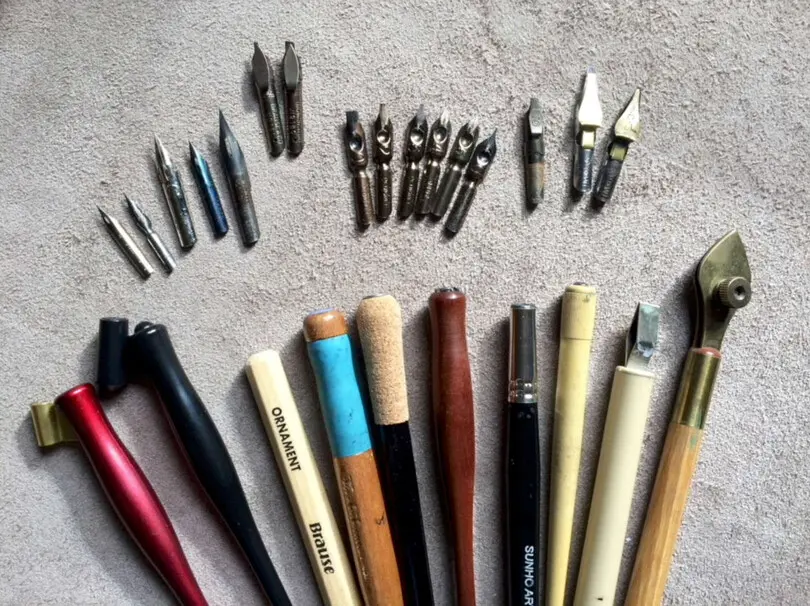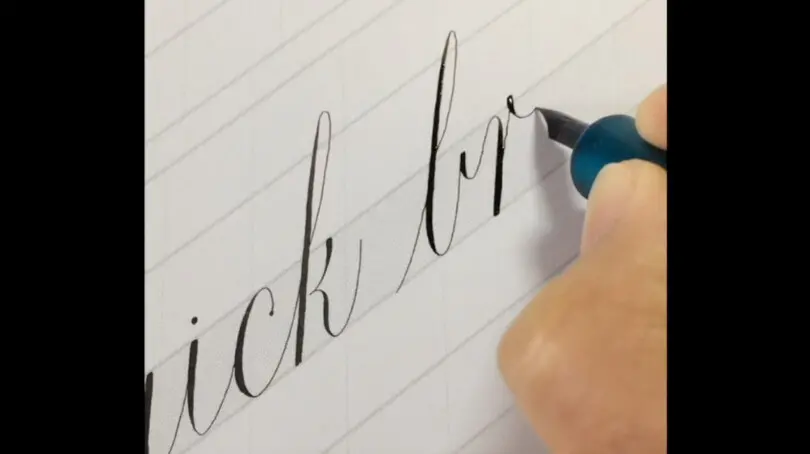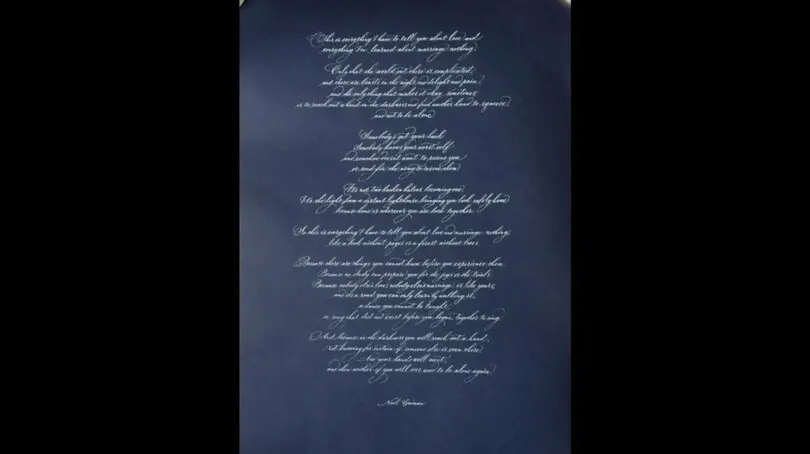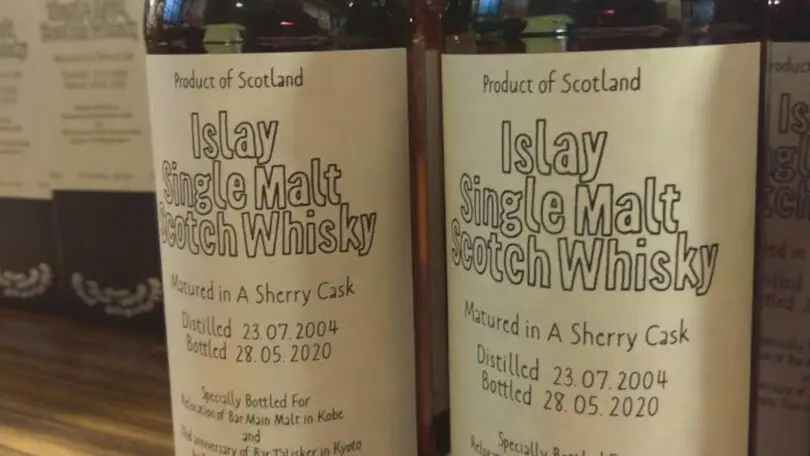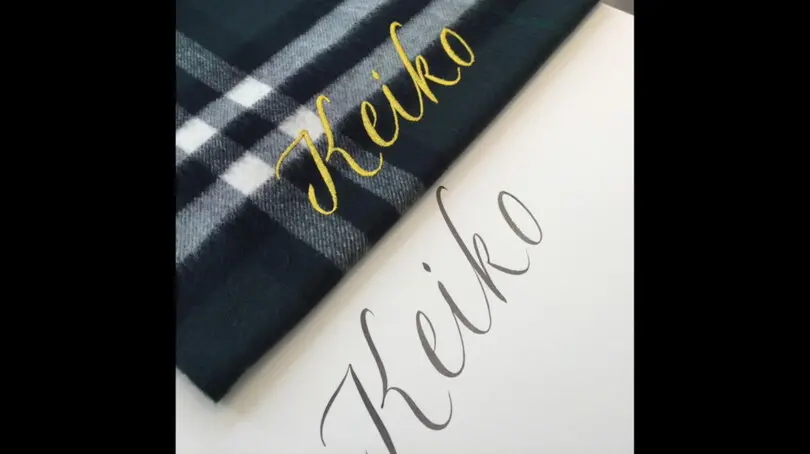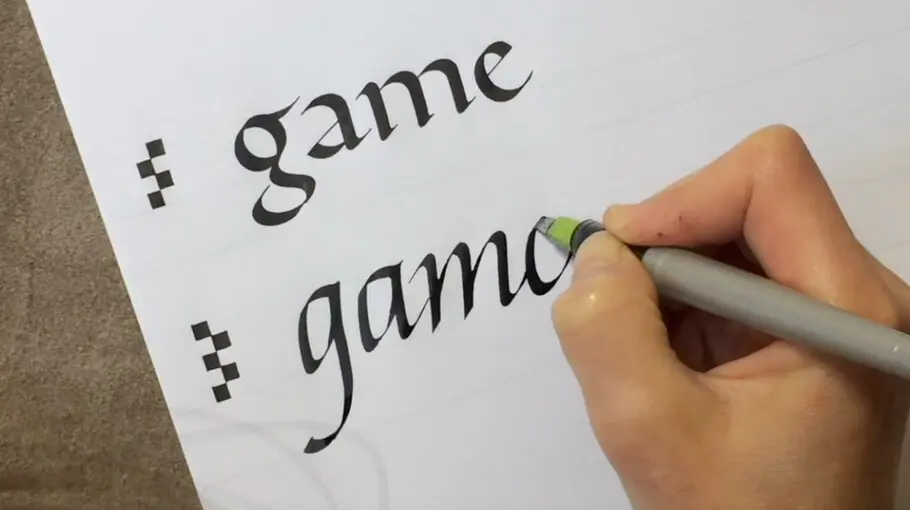
文字は手で書くことから生まれる
カリグラフィーの仕事
ロンドンで文字を書く仕事をしている下田恵子氏。2010年からフリーランスとなり、ファッション、イベント業界をはじめ、パッケージデザイン、映画業界などで、日本の書道と西洋カリグラフィーの文字を書く仕事をされています。
このセッションでは、カリグラフィーで書かれた本とその歴史、道具、普段の下田氏のお仕事の事例を見せていただきました。
冒頭では、カリグラフィーで書かれた本を写真で紹介。ブリティッシュ・ライブラリーで見られる本のほか、橋口恵美子氏(下の写真は橋口氏の作品)、深谷友紀子氏、グドルン・ツァップ氏の本が紹介されました。
カリグラフィーには2000年の歴史があり、ルネッサンス期までは文書保存の唯一の方法で、本を作る技術の一つでした。中国からヨーロッパに紙が届くまでは、羊皮紙が使われていましたが、とても高価で、金属のペンができるまでは、植物の葦や白鳥、雁などの鳥の羽を切って作ったクイルが使われていました。
15世紀後半に印刷が普及すると、文字を書く仕事が激減し、カリグラフィーはほぼ消滅します。20世紀のはじめ、イギリスのエドワード・ジョンストンが古くから残っていた文字を分析して、幅広ペンを使って字を書くことを再発見し、現代のカリグラファーの基礎を作りました。幅広ペンで書く文字のほか、早く書くために生まれたイタリック体や先がとがった金属のペン(ポインティッドペン)で書くカッパープレート体などがあり、下田氏が写真を見せながら解説してくださいました。
後半は実際の仕事の紹介。下田氏の仕事の依頼主は、ファションやイベントの会社、パッケージやグラフィックデザイン、教会や団体などに分けられ、それぞれの目的によって求められる字のスタイルが違います。イベントやファッションショーなどで使われる字は見栄えがよい筆記体の受けがよく、一方、認定証などの字は、読みやすいしっかりとした飾り気のない字が求められることが多いそうです。
例えば、この作品は、結婚1周年の記念に結婚式で読まれたリーディングを書いたもの。お客様が最初に希望したのはあまり堅苦しくならないように少し崩したような字でしたが、これで長い文章を書くと1行が長くなり、行間を大きめに取らないと希望の紙のサイズに収まらなくなります。そのため、字の間が狭く、アセンダーとディセンダーが短く、フォーマルなラウンドハンドよりはゆるめのスタイルを提案。
カリグラフィーは、コンピュータで作ったものより時間も値段もかかりますが、そういう不完全さも含めて⼿を使って書かれたものに価値があると考えています。⼀つ⼀つの字を活字のように完璧に同じに書くことはできませんが、単語や⽂章作品全体として⾒た時に⼼地よいリズムや統⼀感を持たせることを目指しています。依頼主一人一人の思いや背景を知り、その人にゆかりの要素を取り入れ、その目的に沿った仕上がりになるように努めます。完成までに何度もやり取りし、微調整も可能なので、オーダーメイドでその人専用の何かを作るようなものなのです。
書道もカリグラフィーも誰かの手から出てきたものです。習字の基本は模写。昔の字をコピーして練習して自分のものにしていきます。「同じ古筆を見て臨書しても個人個人の目を通して違う脳に入り、違う手を通して出てきた時点で、まるで同じ字は存在しない」と習字の先生がおっしゃっていました。きれいに見えないのにわざわざ手で本や文章を書く意味は、個人差も含めて手で作ったものにある魅力ではないでしょうか。
個人からではなくデザイン事務所などから商業用として字を求められることもあります。最近は手書き風の文字が求められることが多いです。書いた字は素材の一つとして、既存のフォントなどと組み合わされて使用されるので、その後のプロセスを知らないことが9割。逆に、依頼主が欲しい完成図がはっきりしている場合もあります。ウイスキーのラベルデザインの仕事では、完成したラベルのイメージが先にあり、「こういう字が良い」と選んでいただいた後で字を書きました。
字をデータとして渡すのではなく、実際の物に直接書く場合もあります。表面が光っている紙、ビニール、プラスチック、メタリック、あまりにも凸凹すぎる面に書く場合は使うペンや筆が限られます。また、書いた字をスキャンしてカシミアに刺繍した時は線の太さや大きさが制限されました。こういう場合は、できる、できないを依頼主に説明するのも書き手の責任になります。
ロンドンで日本の字を書いていて、おきる問題もあります。映画のセットで日本語の文字を書く仕事をした時、「ちょっとここに何か書いておいて」と気軽に言われましたが、漢字を読めてしまう人にとっては1文字でもそれが情報になってしまいます。文字は情報伝達の道具であって、模様ではありません。カリグラフィーの作品でも、こちらの人は何が書かれているのか読もうとするので、人に伝えたい場合は読みやすいように文章の改行箇所に気をつけて書くようになりました。作るものの最終目的や言葉や文章の意味を考えると、違うようにとらえることができるような気がします。
カリグラフィーで、オススメの本はありますか?
太古の昔から現存している書跡を集めて、図版で見せ、歴史を紹介。特徴を解説。先史時代から15世紀のイタリックまで。ポインテッドペンは含まれていませんが、図例が多いです。
ポインテッドペンはこちら。18世紀にビッカムにより彫られた銅版の画像集。大文字の種類やフローリッシュ(飾り)の種類も多いです。コピーしているだけで勉強になります。
エドワード・ジョンストン直系のカリグラファー、アイリーン・ウェリントンの作品を多数収めた本で、彼女の作品へのアプローチや、実際の仕事例などを教え子たちなどがまとめたもの。創作作品をまとめる時や、数多い情報を一面にまとめる仕事の参考に。
日本語の本では、三戸美奈子先生が書かれた『カリグラフィーブック』(ISBN 978 4 416 81153 5)(『カリグラフィーブック増補改訂版』 ISBN 978-4416717325)がとてもよいです。歴史から道具、字の形、書き方、まとめ方、とても分かりやすいので、今から始める方にはおすすめです。
なぜ今回のセッションを企画したのでしょうか?
(小林)手を使って文字を生み出し、その文字が意味を持って相手に伝わることが大事です。デジタルフォントとカリグラフィー、お互い敵同士ではなくて、たまたま道具が違うだけで、結局は文字の形、単語の形、文章を届けて相手に伝わることなので、ゴールは一緒。手でものを作る時の微妙な調節の仕方で文字が生きる、線が生きることが重要だとわかってもらえるといいですね。ラウンドハンドで「Calligraphy」と書くと、2つ目のエルがちょっと高くなるのですが、この微妙な違いが文章になった時に生き生きしてきます。フォントの場合も、カリグラファーのペンや石彫りのノミを動かす時のように、ここに気をつければ読みやすくなるというのは同じです。
(下田氏)フォントも人の手を介してできているもの。最終目的がなんなのかによって、カリグラフィーよりもフォントの方がきれいに見えることもありますが、共通点もたくさんあります。
大切なのは目を訓練するということですね。目が訓練された後で、手が動いてくれないといけないので、そことの戦いです。頭でわかっているのに、手が勝手に動くこともあり、「脳と筋肉の戦い」になります。
カリグラフィーはそんなに敷居の高いものではないので、興味がある人はちょっと書いてみて、はまってもらえたらうれしいです。